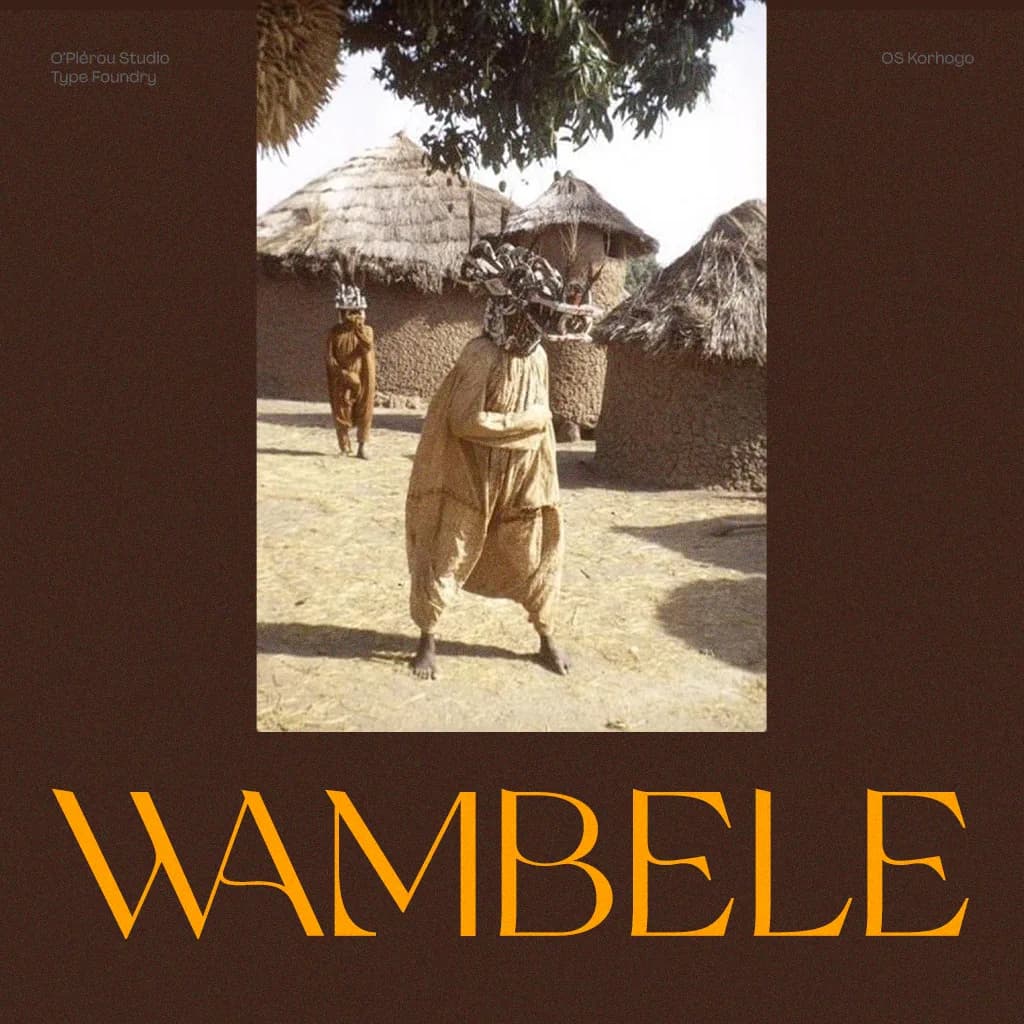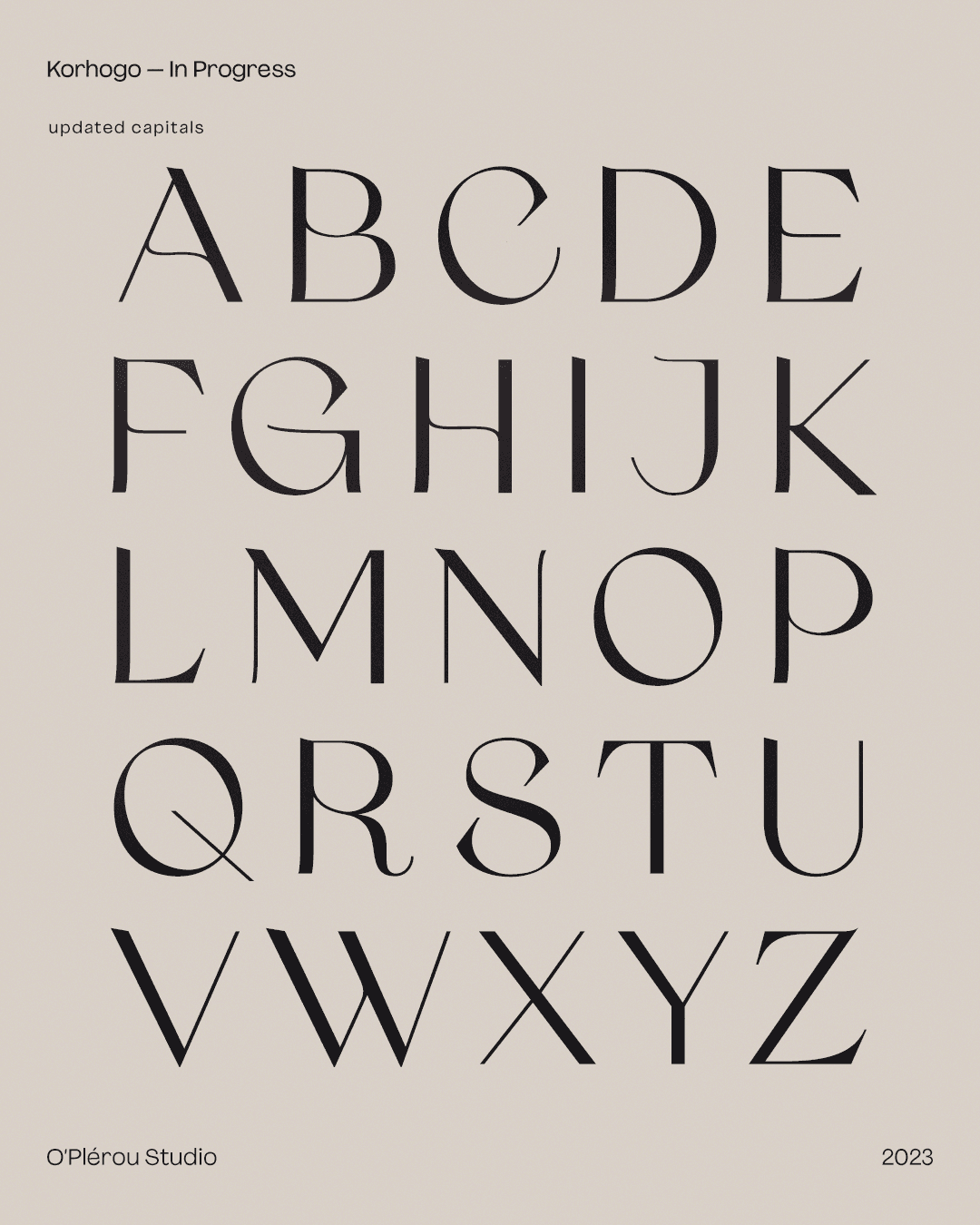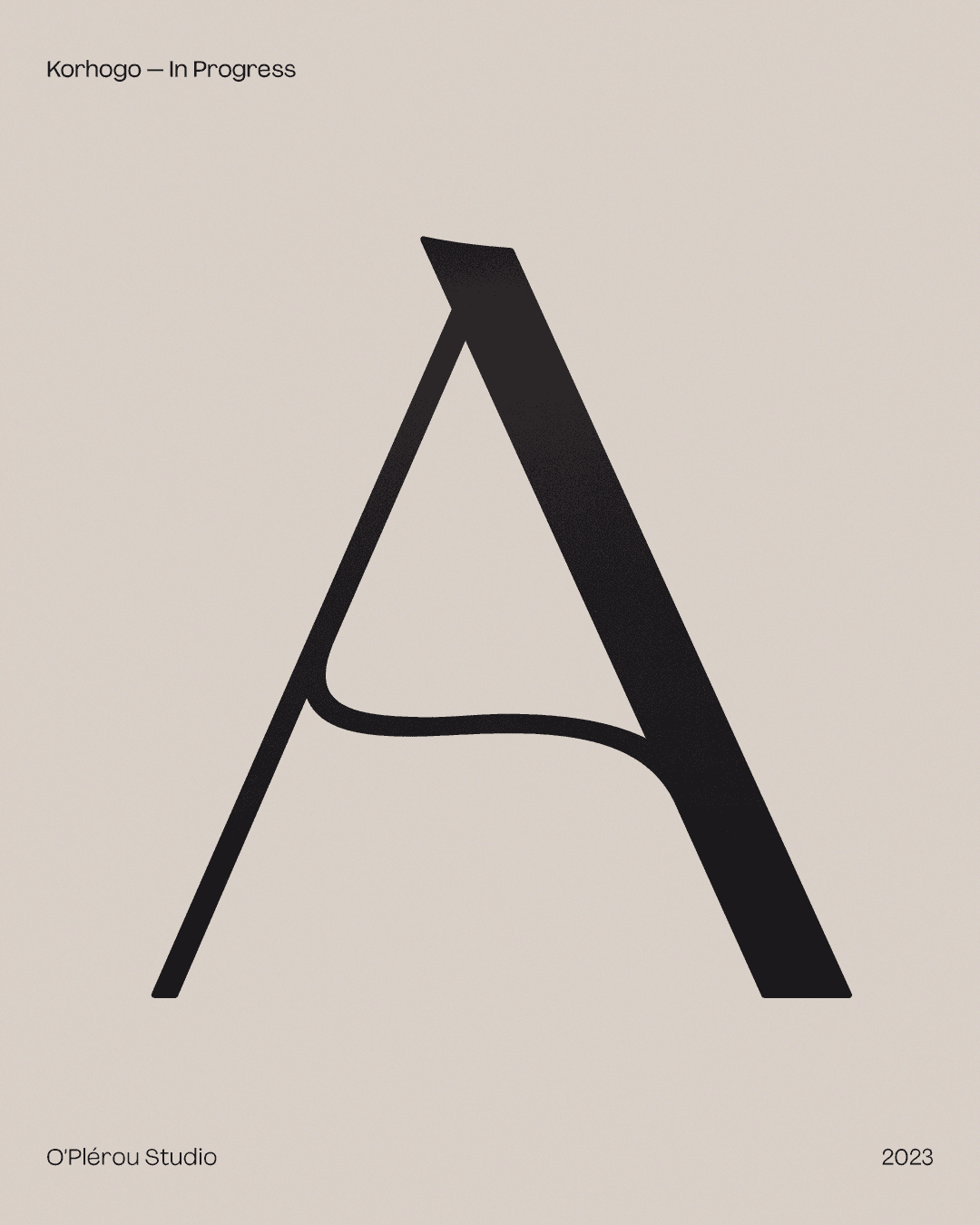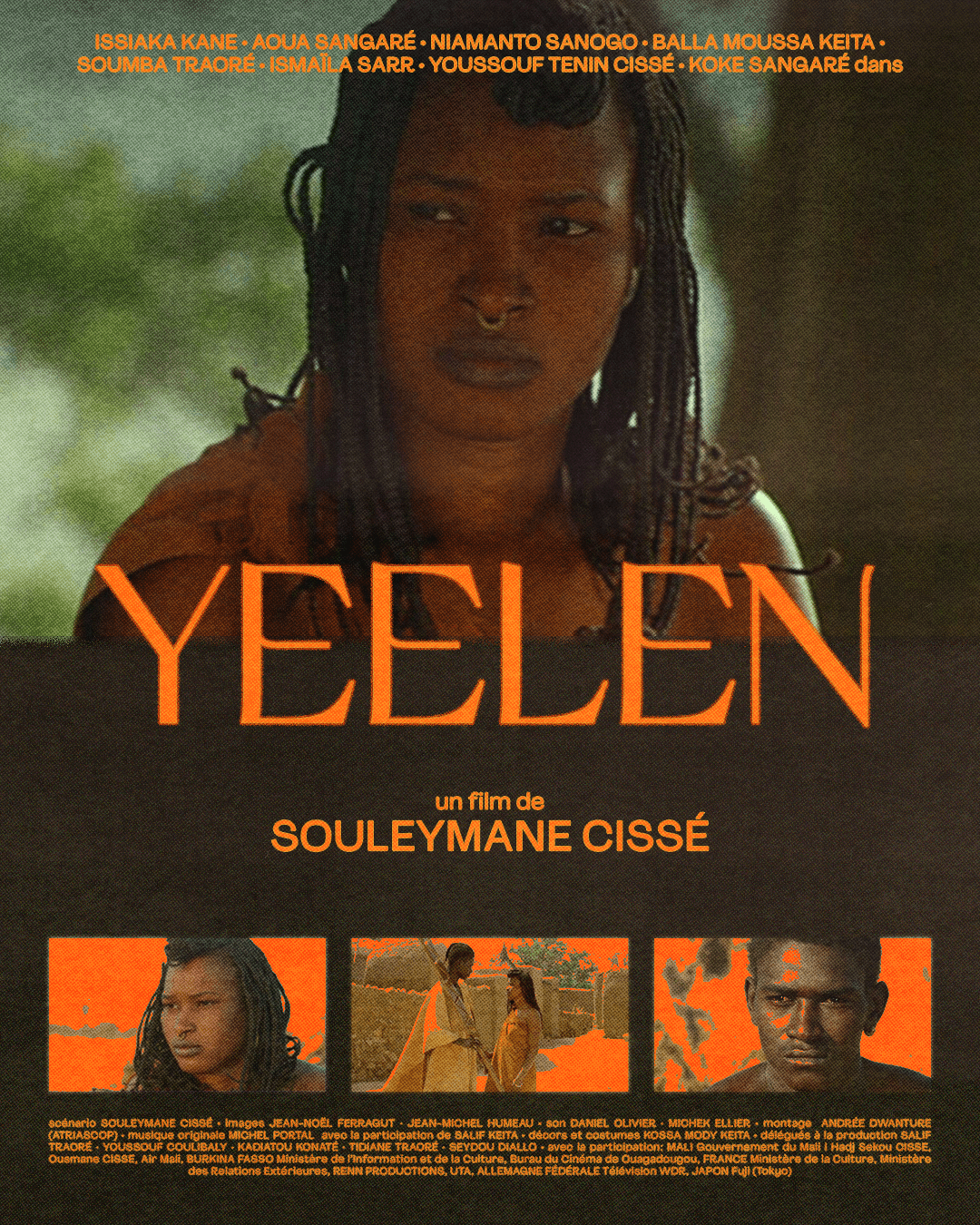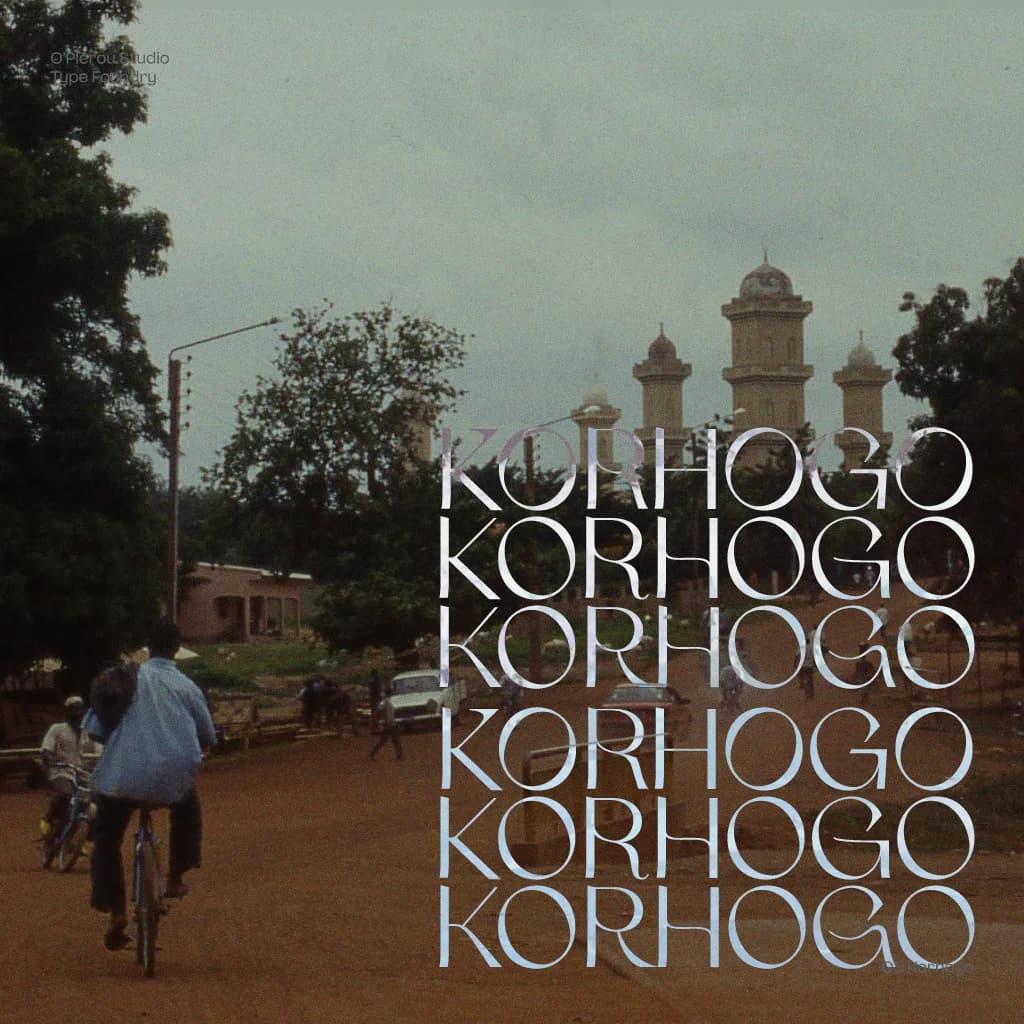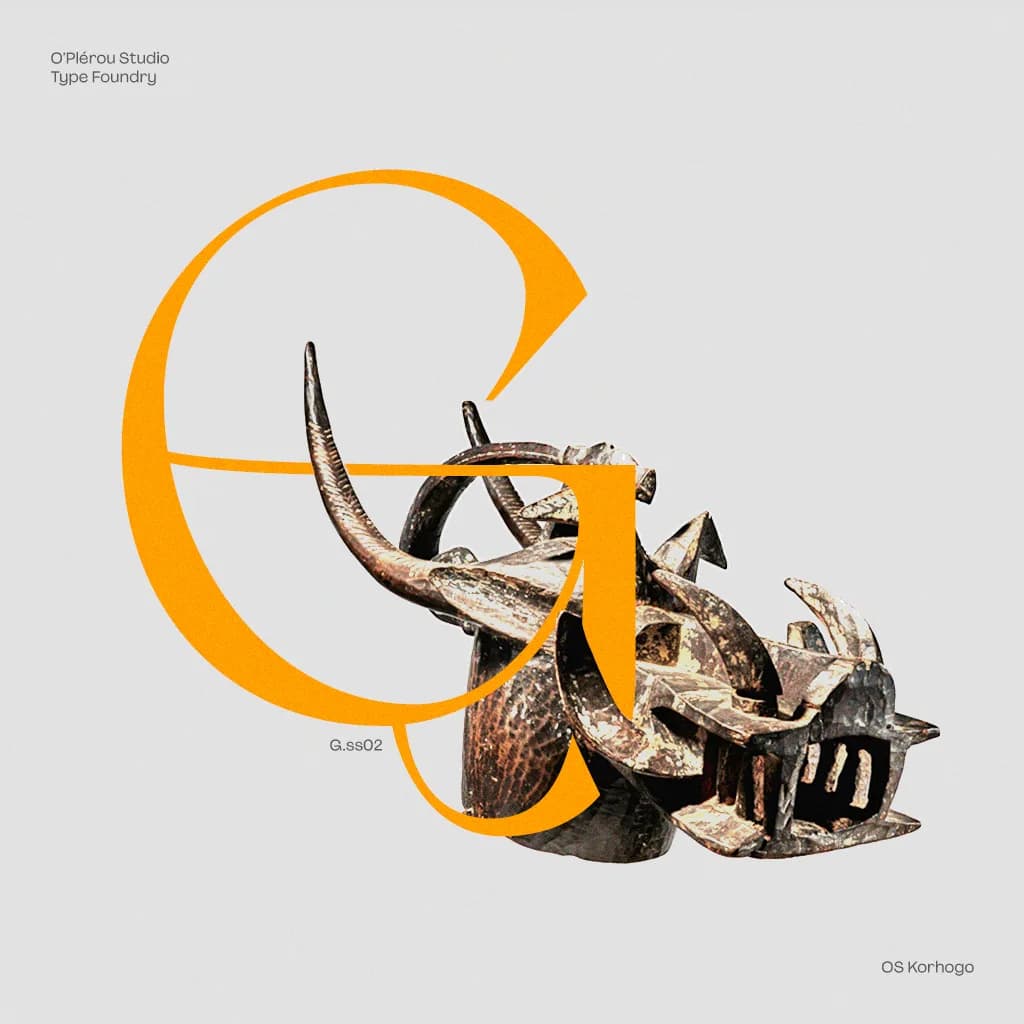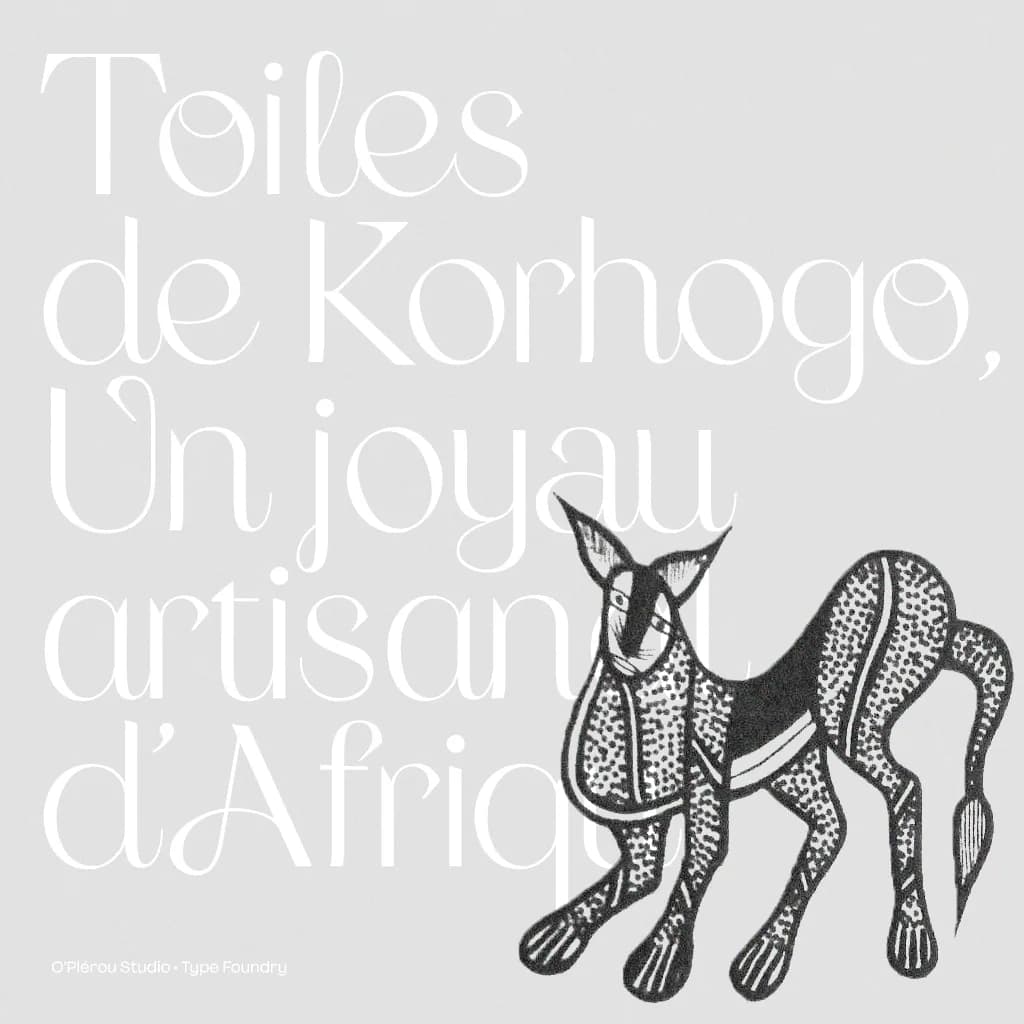
OS Korhogo Forgeron
Inspirée par la puissance de la forge.
Dessinée depuis 2021, Korhogo Forgeron est une ivographie expérimentale ayant évolué avec le temps, explorant l'antre du métal, le feu de la forge et la sculpture sacrée de la matière. Le forgeron Sénoufo dompte la matière par la force du bras et la chaleur des braises; c'est cette puissante maîtrise transformant le métal en art qu'active cette police. Dédiée à Koni, village de forgerons au nord de Korhogo.